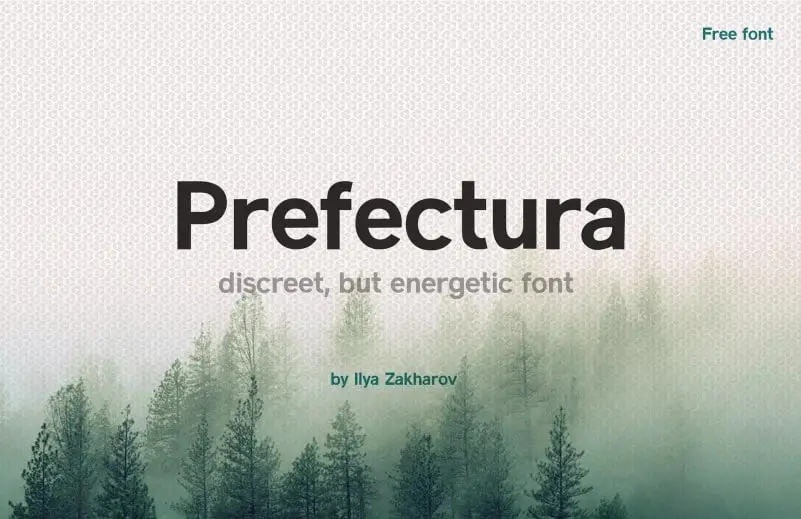
Prefectura Sans Serif Font – Download Grátis
Prefectura Sans Serif é uma fonte moderna e distintiva do tipo sans serif. Com seus versões alternativas, oferece soluções ricas para os projetos criativos. Você pode criar seu texto utilizando caracteres normais e destacar caracteres mais estilizados e títulos. Através de suas inúmeras funcionalidades OpenType, suporte a múltiplas línguas e letras em minúsculo maiuscula, ela se destaca pela sua ampla área de utilização comparada às fontes similares. A Prefectura Sans Serif é especialmente adequada para aplicações como embalagens, rótulos, designs de rotas, aplicativos móveis, criação de marcas e logotipos. Ela também se encaixa perfeitamente em todas as apresentações e edições, bem como trabalhos impressos tanto indoor quanto outdoor. Com essa fonte na sua coleção, você terá uma aliada versátil para projetos que exigem estética moderna e recursos profissionais de design. Seja um designer gráfico iniciante ou profissional, a Prefectura Sans Serif estará pronta para oferecer os recursos necessários para tornar seu trabalho mais impecável e criativo.